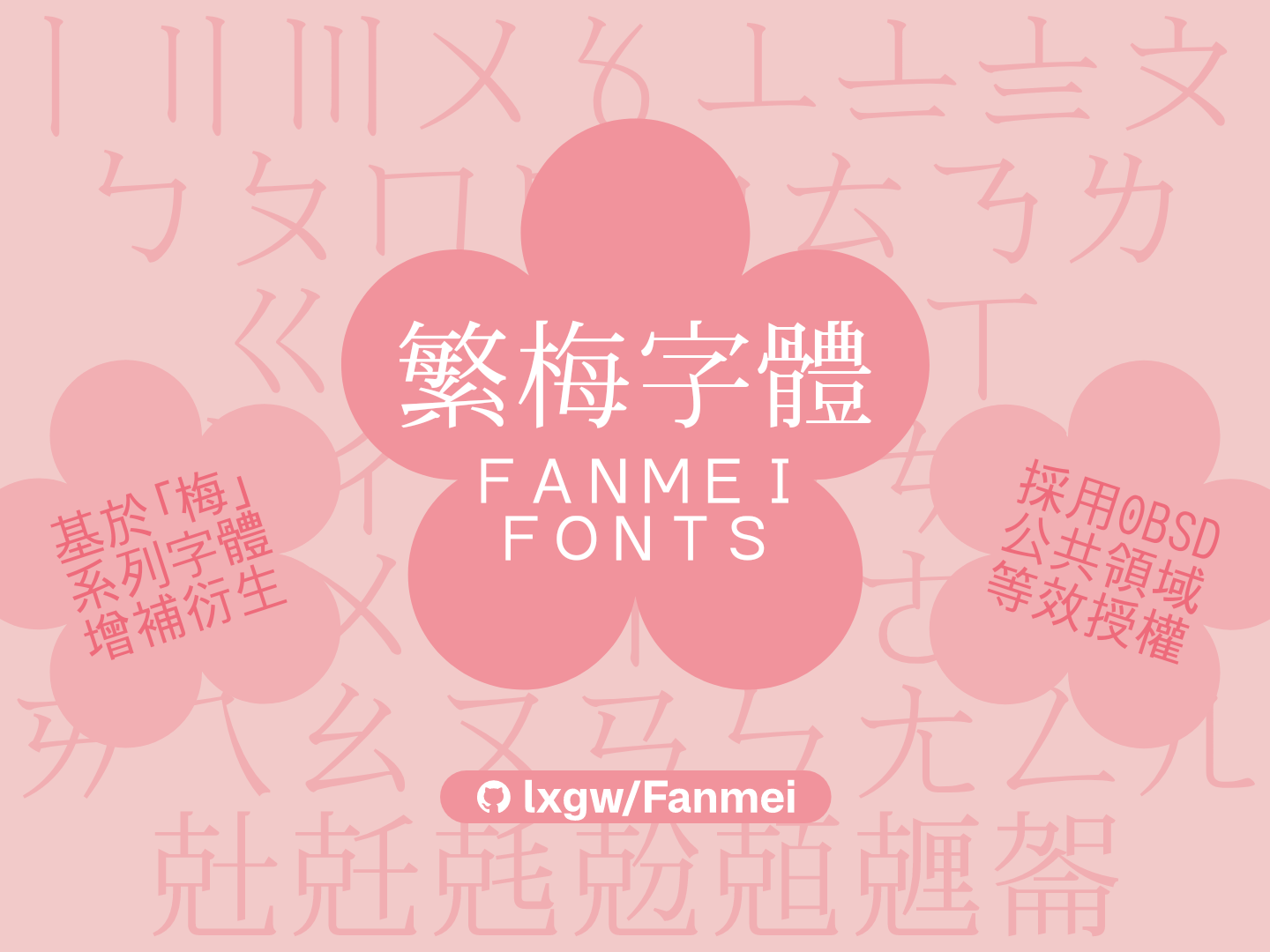
“繁梅字体/Fanmei Fonts”是“梅系列字体/Ume Fonts”的补充项目,包含两种字体:繁梅黑体/Fanmei Hei 和繁梅明体/Fanmei Ming。这两种字体都是基于“梅ゴシック/Ume Gothic”和“梅明朝/Ume Mincho”这两种字体进行扩展而诞生的。
该项目补充了 BIG5 标准中的常用汉字、注音符号以及苏州码。同时,对部分具有明显日式风格的字形进行了调整(如“僧”“抱”“汉”“耀”等),并新增了 950 个编码页面支持。此外,将 U+005C 符号原来的 ¥ 符号调整为 \ ,标点符号也进行了调整,使半宽方块符号所表示的字符、箭头、部分几何图形符号以及各类符号都采用了全宽形式,以符合繁体中文的使用习惯。
在调整标点符号时,被替换下来的原有符号被收录在“小型标点符号变体”部分。此外,还可以通过 Unicode 标准变体序列来调用这些符号(例如,“,”默认位于中间位置;使用变体选择符 U+FE00 后,其位置会改为左下角。更多支持的序列请参考此处)。在调整汉字时,被替换下来的日文风格字形可以通过 locl 特性在日文环境中使用。查看主要的补充字符
注意事项
- 目前的字形补充仅包含 BIG5 常用字,后续可能会根据情况再补充“jf7000 当务字集”的基本包以及粤语扩展包。除此之外,目前没有进一步补充字形的计划,也没有制作简体版的计划。
- 这些字体的调整仅限于使用 BIG5 标准中的常用字符,且只针对那些具有明显日式风格的字形进行修正。除了某些需要统一处理的部首(如辵部、戶部、示部、食部等)之外,其余部件都保留了多样性,不要求各部件完全一致,同时遵循 Unicode 的“字源分离”原则(例如“值/値”、“巓/巓”、“飲/飮”等字形仍保持差异)。
- 为了保持字体风格的一致性以及提高维护效率,本字体仅提供等宽版本,方便用于代码、表格等排版场景,不提供比例缩放功能。